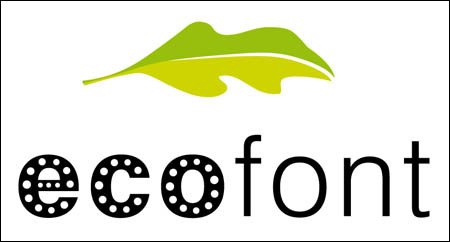
Ecofont, il font ecologico che risparmia l’inchiostro
EcofontStampiamo, poi leggiamo, infine appallottoliamo e centriamo il cestino. Immaginate quante persone ogni giorno sprecano la carta così. Si stima che un lavoratore americano medio, stampi ogni anno 54 kg di carta! E allora ci si deve dare da fare utilizzando carta riciclata e, soprattutto, evitando di stampare quando non è necessario. Ma il risparmio ci può essere anche sull’inchiostro grazie ad Ecofont: un font che consente di ridurre il consumo di inchiostro.
Ecofont è un carattere tipografico ecologico e gratuito che fa durare le cartucce delle stampanti il 20% in più. Ma come è possibile? Il trucco c’è ma non si vede! I caratteri di Ecofont, sono caratterizzati da minuscoli cerchietti vuoti, dei forellini invisibili all’occhio quando il testo è stampato in dimensioni normali, che fanno in modo che per ogni lettera sia necessario meno inchiostro. Ecofont, scaricabile gratuitamente online, rende eco tutti i più comuni caratteri tipografici (Arial, Verdana, Calibri…) fino alla dimensione di 11 pt, dotandoli di piccoli fori.
Pensate a che risparmio di inchiostro si avrebbe se adottassero questo font ecologico le testate giornalistiche, gli uffici comunali e le case editrici! Inizia anche tu a risparmiare inchiostro: Ecofont è gratuito, scaricalo qui